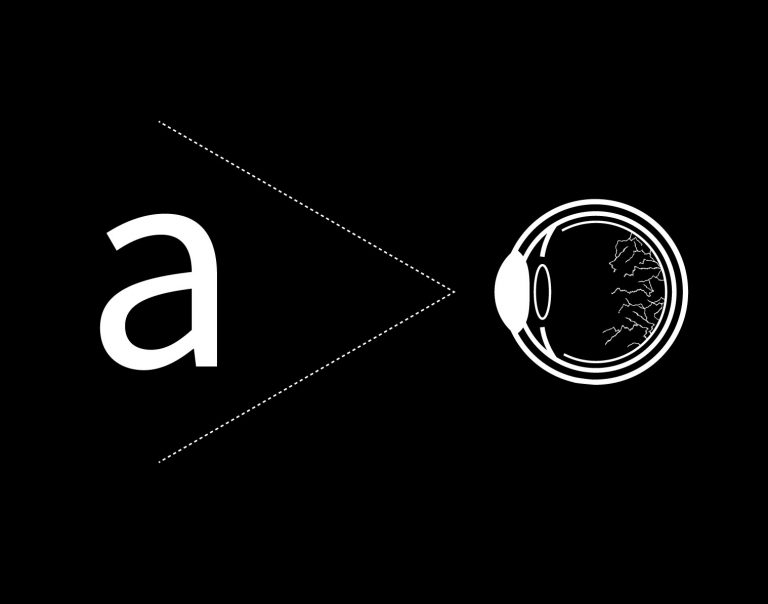
¿Qué sucede cuando el posible receptor de un objeto visual como el diseño gráfico sufre discapacidad visual?
Para los ciegos existe el Código Braille, que como todo el mundo sabe, es un sistema pensado para ser leído con los dedos, es decir, táctil, no visual. Pero, además de personas invidentes, existen un sinfín de personas afectadas por toda clase de retinopatías que merman seriamente su capacidad visual. «Retinopatía» es un término médico que se refiere genéricamente a cualquier dolencia no inflamatoria de la retina, la membrana interna del ojo que gestiona la luz y la envía al cerebro a través del nervio óptico. Es decir, si la retina se encuentra afectada, esto supondrá una pérdida considerable de visión.
Los órganos de la visión y la tipografía están íntimamente relacionados. El sentido visual de tipografía se ve seriamente interrogado si la visión del receptor está tan mermada que apenas es capaz de distinguir unos signos de otros. ¿Qué sentido tiene la tipografía si no puede cumplir su principal misión, ser leída, es decir, transmitir un mensaje de manera clara? Podríamos pasarnos horas dando vueltas y vueltas a esta cuestión, pero aquí partimos del hecho de que hay personas con problemas visuales y que los diseñadores gráficos podemos hacerles la vida un poco más fácil.
Por eso, nos ha llamado la atención el proyecto de la diseñadora Mar Pérez, Ready, una fuente tipográfica diseñada para que resulte accesible a personas con discapacidad visual. Ready, a nuestro modo de ver, supone una muy interesante manera de abordar el diseño tipográfico, pues lo hace desde la raíz, es decir, estudiando la naturaleza visual del objeto tipográfico y, lo que resulta más importante, la fisiología del ojo, su estructura y funcionamiento, y el modo en que incide en la visión las afecciones que afectan a la retina.
Bocetos de Ready. Imágenes cedidas por Dsigno.
Para este proyecto, Mar Pérez, creativa de extraBold Creative Studio, ha estado en contacto durante todo el proceso de creación de la Ready con personas afectadas por retinopatías que han ido comprobado la eficacia del proyecto paso a paso. Un proyecto que por su propia naturaleza debía partir de premisas muy concretas; el diseño gráfico como vehículo para un fin. En este caso, conseguir una fuente tipográfica ultralegible y adaptada a personas con problemas visuales serios. Un reto muy sugestivo conceptualmente.
Ready es una palo seco que busca ser los más neutra, clara y limpia posible, centrándose sobre todo en ser altamente legible, para lo cual se ha buscado equilibrar los blancos internos y externos; legibilidad y lecturabilidad ante todo.
Tipografía Ready. Imágenes cedidas por Dsigno.
Ready se ha diseñado exclusivamente para la exposición «Rietveld reimaginado», organizada por la escuela de diseño DSIGNO el próximo 1 de julio en las instalaciones de DIMAD, en el Matadero de Madrid, para conmemorar el centenario de la «Silla Roja y Azul» de Gerrit Rietveld.
Todo el proyecto de la exposición «Rietveld reimaginado» para el que ha sido creada la Ready está impregnado del concepto de adaptabilidad del que también parte la tipografía de Mar Pérez.
Conceptos como «accesibilidad física», «diseño universal» o «diseño para todos», acuñados por el arquitecto, diseñador y profesor Ronald L. Mace sirven de punto de partida para reflexionar sobre las verdaderas utilidades del diseño y cómo éste puede ayudar de manera fundamental a crear un mundo más inclusivo, en el que ninguna persona sea marginada por razones de discapacidad física o enfermedad. Se trata, en palabras del propio Mace, de la «creación de productos y entornos diseñados de modo que sean utilizables por todas las personas en la mayor medida posible, sin necesidad de adaptaciones o diseños especializados». De este modo, la tipografía Ready, con la que se rotulará todo el evento junto con el sistema Braille para personas ciegas, cumple con las premisas de que el diseño es una herramienta para dar solución a una enorme diversidad de problemas cotidianos, en este caso, de comunicación gráfica.
Funcionalidad y estética no son conceptos incompatibles, en absoluto. En la amplitud del diseño gráfico y tipográfico caben multitud de proyectos ya sean destinados a un fin específico, como es el caso de la Ready, como otros de carácter más especulativo que, como hemos dicho en alguna otra ocasión, buscan exclusivamente el placer estético, la gozosa reinterpretación de las formas de la letra. Ambos conceptos son necesariamente complementarios, pues, naturalmente, funcionalidad y estética son los dos ejes del diseño, como queda bien patente en la obra del homenajeado Gerrit Rietveld y su icónica silla.